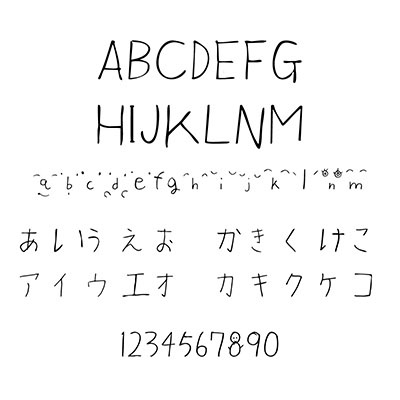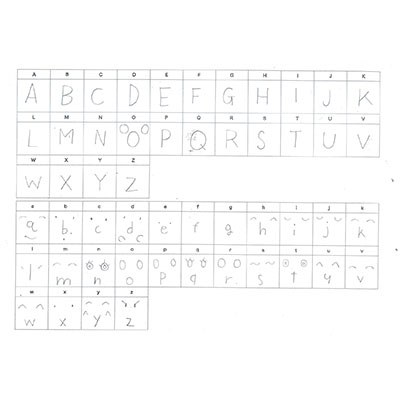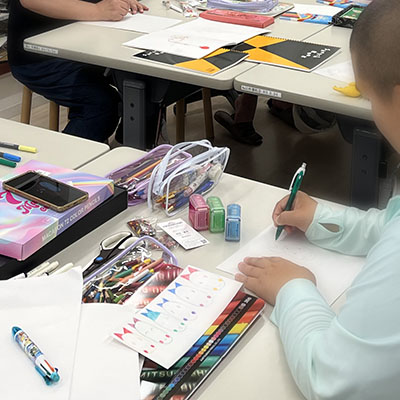
笑顔にこにこ
楽しく描けました!(春田ミカ)
初めて原画を見たときは「自由すぎる!」と驚きました。いい意味でフォントの先入観が崩れました。アルファベットのサイズ感を調整するのが難しかったですが、なるべく原画の手描き感や自由な表現を保つことを意識しました。(クロ)
アーティストの可愛らしいイメージがそのままフォントになってとても嬉しいです。(NPO法人GreenWind)